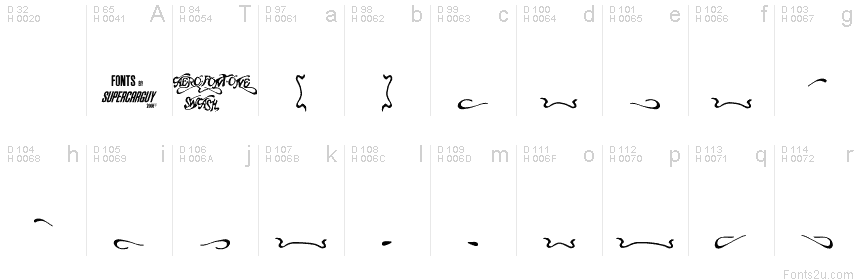
Aero Font One Swash od Supercarguy to darmowy, dekoracyjny krój pisma, który wzbogaci Twoje projekty o efektowne zawijasy bez konieczności męczenia się ze skomplikowanymi ścieżkami wektorowymi. Jego płynne linie przypominają szybkie, pewne pociągnięcia pędzla — są wyraziste, atramentowe i mają w sobie tę nutę naturalnej niedoskonałości, dzięki której wyglądają jak odręczne, a nie wygenerowane komputerowo. Wystarczy podłożyć te ozdobniki pod słowo lub wokół logotypu, aby błyskawicznie uzyskać wykończony, unikalny wygląd, który normalnie wymagałby długich godzin ilustrowania.
Dzięki Aero Font One Swash dodasz eleganckie akcenty do zaproszeń ślubnych, logotypów, certyfikatów, opakowań produktów, grafik nagłówkowych czy postów w mediach społecznościowych w zaledwie kilka sekund. Płynny rytm tego zestawu sprawia, że tekst zyskuje bardziej luksusowy i przemyślany charakter, szczególnie gdy połączysz ten darmowy font z prostym krojem bezszeryfowym lub czystym pismem skryptowym. Aby uzyskać najlepszy efekt, ustaw ozdobniki nieco większe niż tekst główny, tak aby go obramowywały, a nie z nim konkurowały.
Aero Font One Swash — Prezentacja czcionki
Supercarguy